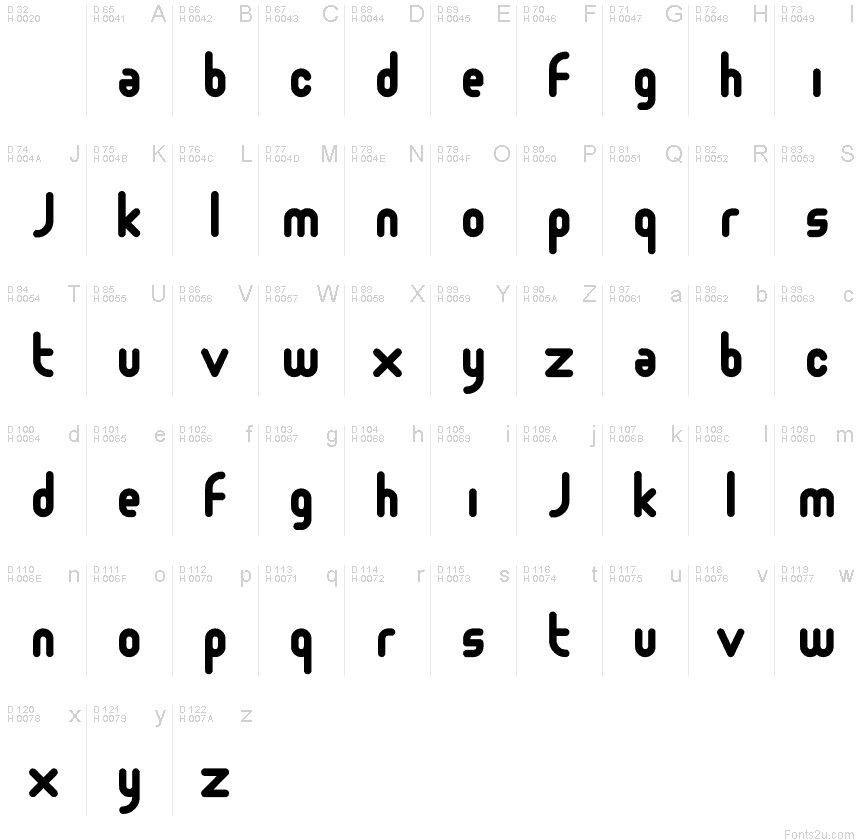
Moloko è un carattere sans serif gratuito con tratti spessi e arrotondati e un ritmo morbido nelle minuscole, che conferisce alle parole una forma fluida e quasi voluminosa. Le curve ampie e le forme semplificate rendono il font compatto e diretto, senza mai apparire rigido.
Moloko è perfetto per titoli di poster, loghi, packaging, copertine di album e grafiche per i social media, poiché la sua struttura arrotondata rimane leggibile pur mantenendo una forte personalità nei formati più grandi. Moloko è adatto anche a citazioni brevi, volantini per eventi e progetti di branding che richiedono una presenza amichevole e decisa, senza bisogno di ornamenti o dettagli complessi.
Moloko